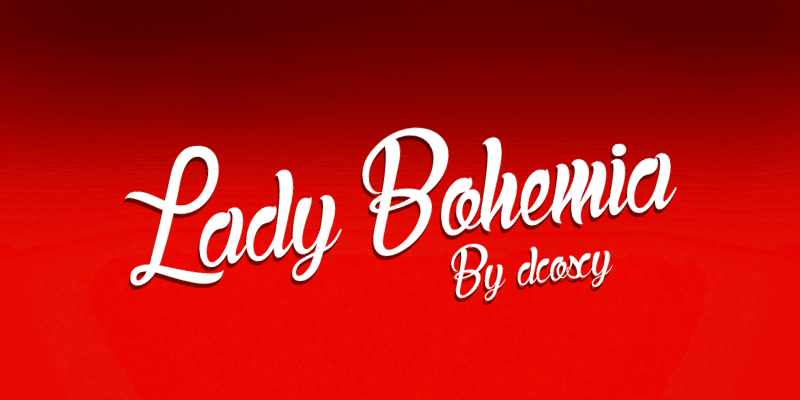
Lady Bohemia Font – Download Grátis
A Lady Bohemia Font é uma elegante fonte tipográfica que se destaca pela sua textura delicada e linhas arredondadas. Inspirada nas artes decorativas do início do século XX, esta fonte exala um charme único que combina elementos de códigos de estilo gótico com nuances da calligrafia moderna. Perfeita para designers interessados em adicionar um toque autêntico e elegante às suas criações, a Lady Bohemia é uma escolha ótima tanto para projetos comerciais quanto promocionais. Recomendada principalmente para texturas legíveis de grandes fontes até médias, esta fonte oferece uma maneira sofisticada de incorporar um pouco do mundo da arte em seus trabalhos, tornando-o ainda mais interessante e único. Não se esqueça de entrar em contato com o designer, Hamilton, antes de utilizá-la comercialmente.